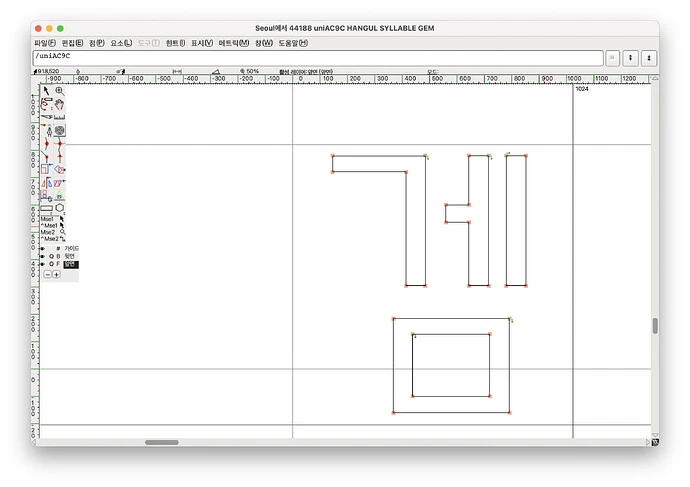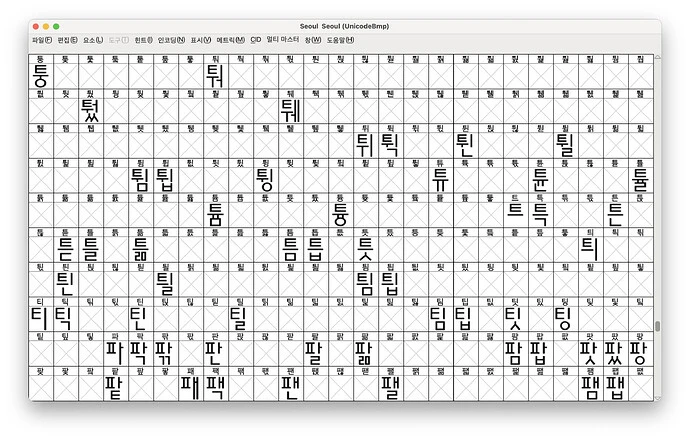
오랜만에 os9의 Seoul 폰트를 열어보며
갑자기 아는 형이 애플 서울폰트를 써보고 싶다고 연락을 줘서 서울체를 이야기하는 것인가 대화를 잠깐해보다 OS9 Seoul 시스템폰트 였던 기억이 났습니다.
사무실에 늘 켜놓는 G5머신이 하나 있는데 거기에 OS9 에뮬레이터가 돌고 있어서 거기서 폰트를 빼서 줬습니다. 그런데 폰트가 비트맵으로 기억하고 있었는데 트루타입도 있었습니다. 오픈소스인 폰트포지로 열어보니 잘 열립니다. FFIL 파일은 Mac OS X 운영 체제에서 사용되는 글꼴 파일로 여러 비트맵 또는 트루타입 글꼴을 포함할 수 있는 글꼴 모음을 저장합니다. FFIL 파일은 시스템 글꼴 또는 사용자 글꼴 폴더에 저장됩니다.
OSX에서 이 폰트를 TTF, OTF를 채용하면서 사라졌죠.
그리고 경로에서 폰트를 빼서
추억이 방울방울… 아주 뚝뚝 떨어집니다.
오픈소스 폰트포지에서 폰트파일을 열어봅니다. 트루타입이지만 비트맵도 포함된 폰트파일입니다. 그래서 100% 제 모양으로 출력되지 않을 것이라 생각되지만 하여간 열어서 폰트를 살펴봤습니다. 별 이상은 없어 보이고 변환해서 사용이 가능합니다.
os7 한글화한 분이 회사 프로그래머… 프로그텀을 만든 분입니다. 이때 썼던 추억이
어찌됐건 폰트는 제대로 변환되어 있고 비어있는 자모 부분을 채우면 추억의 서울폰트를 트루타입니다. 서울시에서 한강, 남산체 이런게 아니라 안상수 탈네모꼴 폰트 비슷한 모양이죠 오픈타입 그것보다 웹폰트로 만들 수 있습니다.
그런데 안예쁠지도 모르겠어요.
올드맥 사용자들에게 웹폰트로 하이텔 느낌을 줄… 읍 그만=3=3=3
그래서 열어서 폰트를 Seoul.woff 생성하고 개인적으로 웹 페이지에 한 번 사용해보기로 합니다. 이따가 css 되면 링크는 따로 올리겠습니다.
https://a9press.com 에 css 적용하였습니다. 폰트를 바꿔서 배포하는 것은 엘렉스 컴퓨터가 아직 있어서 부담스럽기는 합니다.
크롬에서만 나오고 사파리에서 안나와서 문서 살펴보고 있습니다.